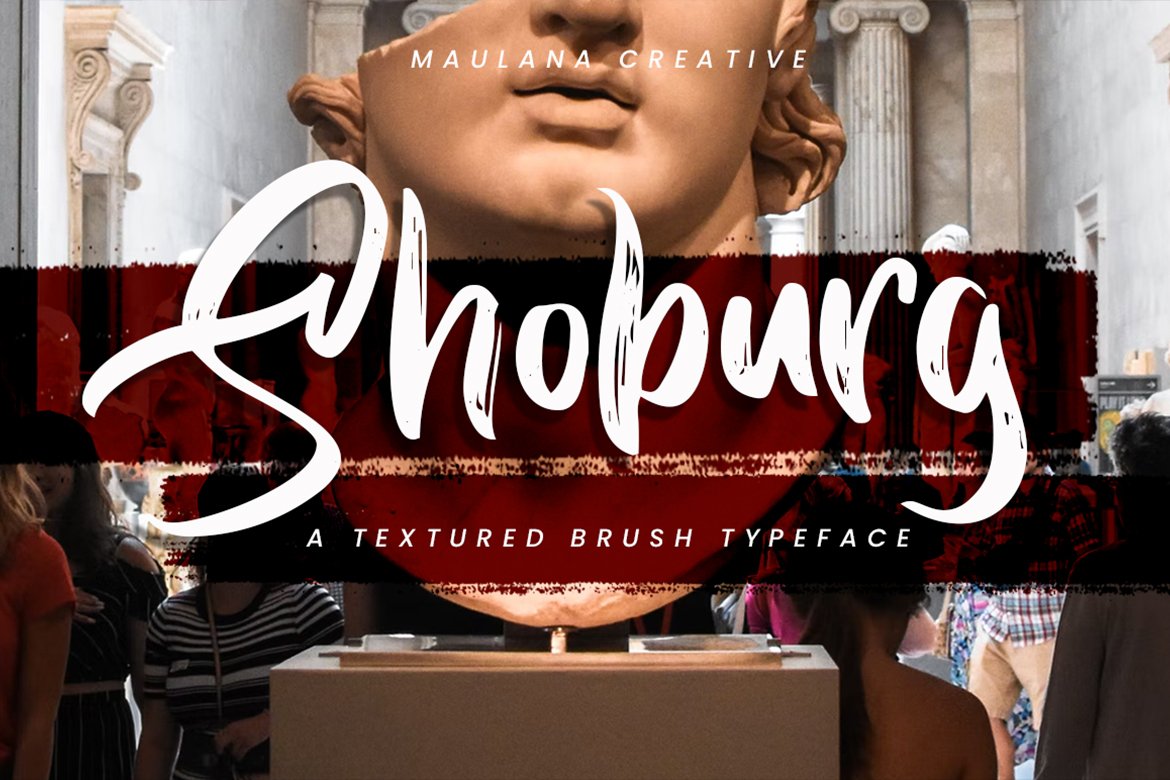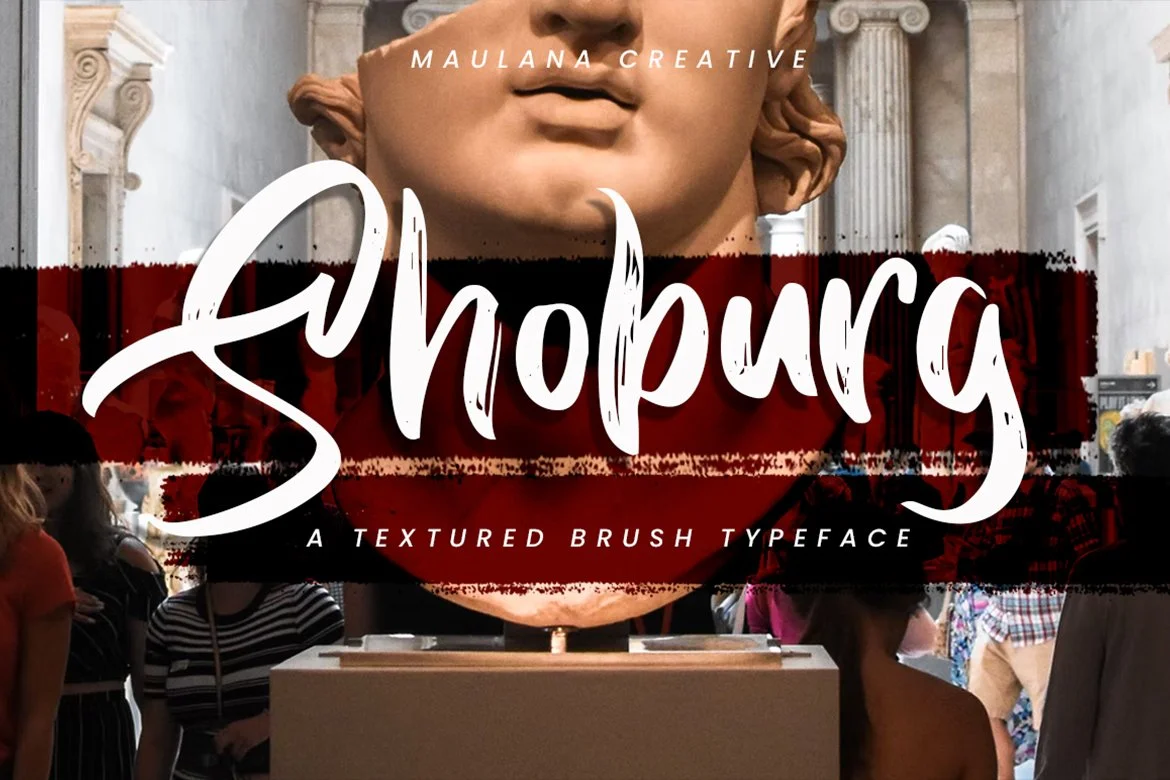
Shoburg - это шрифт с лигатурами и альтернативами. Чтобы дать вам дополнительную творческую работу. Шрифт Crankstock поддерживает более 100+ языков. Этот шрифт хорош для дизайна логотипов, социальных сетей, названий фильмов, книг, короткого текста, даже длинных букв и хорош для вторичного текста шрифтом sans или serif. Сделайте потрясающую работу со шрифтом Shoburg.